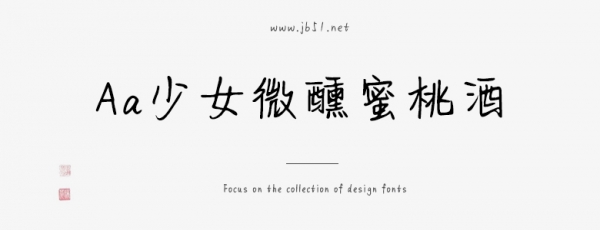
Aa少女微醺蜜桃酒是一款不錯(cuò)的藝術(shù)字體,由Aa字庫(kù)出品,字體筆觸纖細(xì),書(shū)寫(xiě)流暢 ,具有很好的視覺(jué)感,適合應(yīng)用于藝術(shù)設(shè)計(jì)、平面宣傳設(shè)計(jì)、網(wǎng)頁(yè)設(shè)計(jì),書(shū)法字帖等領(lǐng)域,需要的朋友可以前來(lái)本站下載。